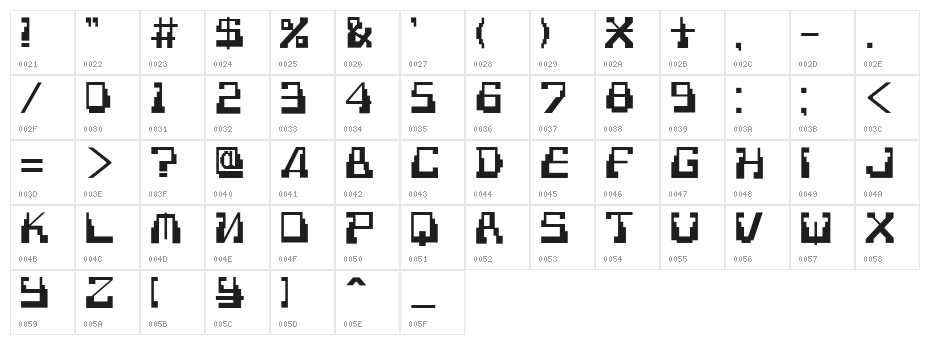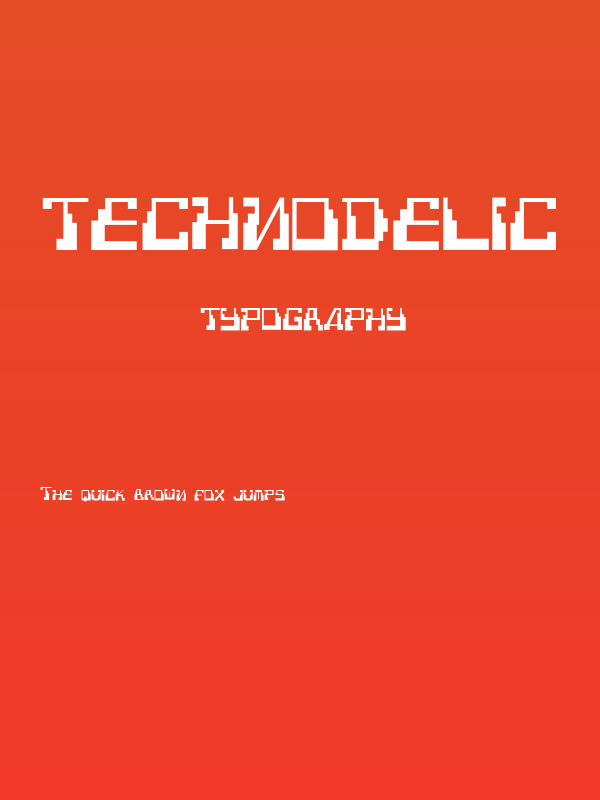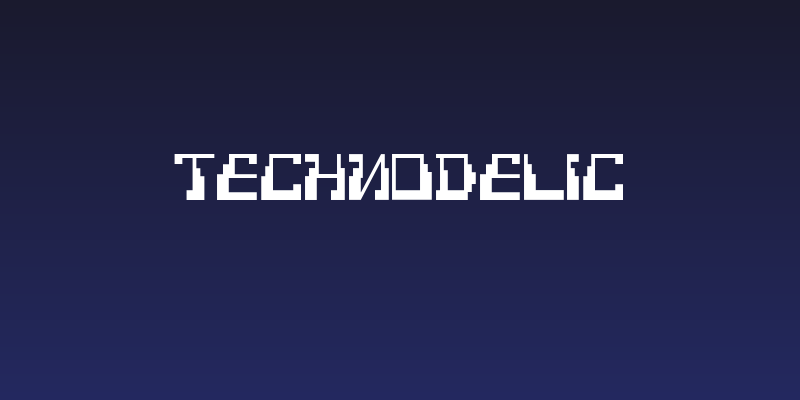
Technodelic Font
| Caso d'uso | Logos, Headlines, Digital Art |
| Progetti proposti | Ideal for tech-related branding, video game design, digital art projects, and modern advertising campaigns. |